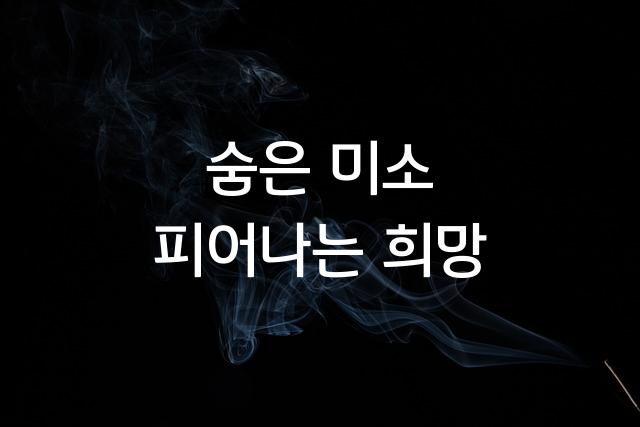
잘풀리는오늘체는 제목용으로 디자인된 둥근 고딕 스타일의 폰트입니다. 장식적 요소가 더해져 시각적 매력을 높이며, 따뜻하고 친근한 느낌을 전달합니다.
잘풀리는오늘체은(는)
별모양/패턴, 길고/크고, 기본 고딕, 복실복실, 부드러움, 감성적인, 장식 스타일, 둥근 스타일 계열의 생김새를 가지고 있으며
초대장, 일기/편지, 인사말 카드 등에서 자주 활용되며, 효과적인 메시지 전달에 적합합니다.
이 폰트는 라이프스타일, 문화/예술, 이벤트/웨딩 분야에 잘 어울리며,
편안한, 부드러운, 친근한 느낌을 담고 있는 것이 특징입니다.